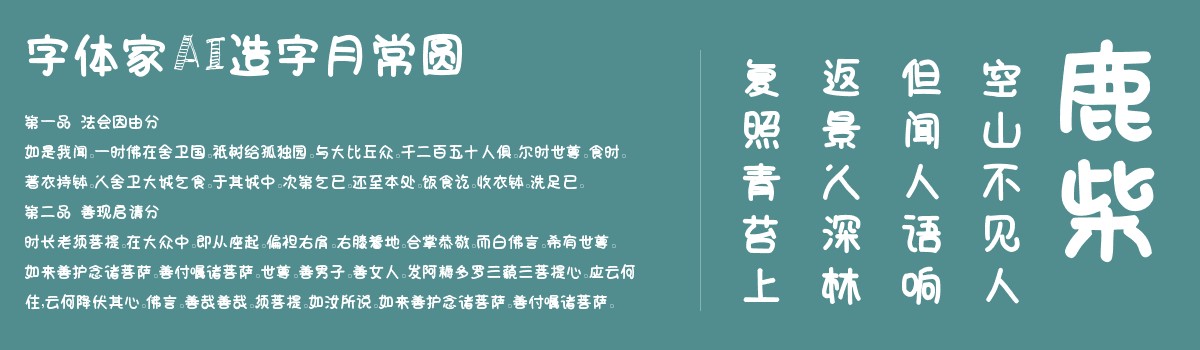
字体家AI造字月常圆
字体家AI造字月常圆是一款由字体家AI神笔造字生成的一款艺术字体,这款字体整体圆润饱满,笔画起收皆呈柔和圆弧,无丝毫棱角,如被月光打磨过的卵石,边缘温润。笔画粗细均匀,无突兀对比,像细腻的丝线围合出的轮廓,柔和不生硬。结构匀称,重心稳稳居中,每个字形都像饱满的圆月,亲切日常,无锐利锋芒,尽显包容温和之美,摸上去该是平滑细腻,没有硌手感,只有融融暖意。比较适合用于艺术类装饰文字,海报、网页、广告设计,室内装饰,平面标题设计、食品包装、品牌标志等。